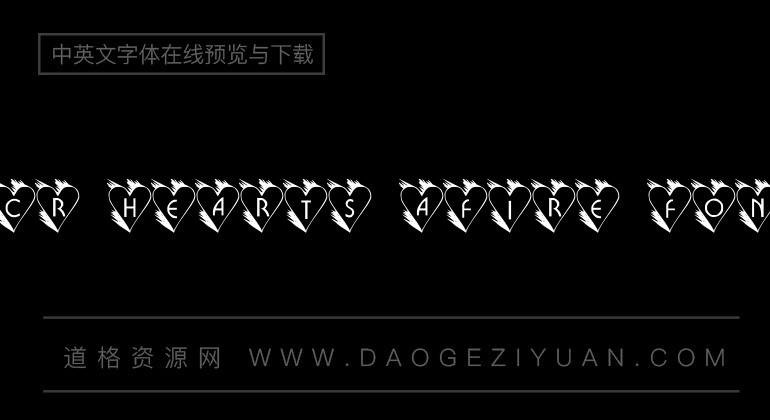
LCR Hearts Afire Font
LCR Hearts Afire Font 是一种装饰性较强的手写字体,它的设计师是美国的著名字体设计师Leah Chong Raggio。这种字体非常适合用于情人节、婚礼、节日、手工制作和其他浪漫场合的设计中。 LCR Hearts Afire Font 的特点在于它的字母有很多花式的装饰,比如说字母的末端有爱心形状的装饰,或者是整个字母的形状就类似于爱心。这种装饰性强的字体在设计中可以起到很好的点缀作用,使得设计更加生动、有趣、浪漫。 LCR Hearts Afire Font 可以免费下载并使用,它支持多种语言,包括英语、西班牙语、法语、德语、意大利语等等。如果你需要一个装饰性强的字体来设计浪漫的场合,LCR Hearts Afire Font 是一个非常不错的选择。
LCR Hearts Afire Font是一款非常不错的手写艺术字体,具有很好的视觉感,适合于文化类的宣传设计、商业类品牌的广告和产品包装设计以及个性化文字排版等较多场景。